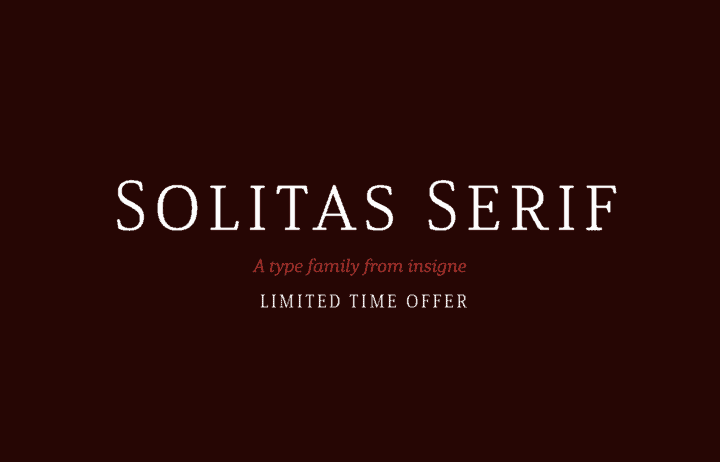
Solitas Serif Font Family
Aqui está uma descrição em português para a página de download da font Solitas Serif: Estou aqui a nova Solitas Serif, apresentada por insigne. Inspirado no design de insígnia, esta serif oferece uma opção mais suave e não tão rígida como outras fontes semifinais. Solitas Serif é perfeito para os designers que procuram um estilo serif menos formal e mais fluido, com serifs leves e bordas redondas. Seja você designer de blogs pessoais ou profissional, Solitas proporciona um toque suave a suas obras. A inspiração vem das curvas da famosa Solitas e do seu estilo semifinaleiro mais robusto (Solitas Slab). O resultado é uma fonte que transmite um charme discreto e contínuo. Este estilo de design oferece ao leitor uma experiência visual agradável, enquanto ainda mantém o bom design de serif que já conhecemos. Descubra agora Solitas Serif – sua próxima escolha para trabalhos profissionais ou criativos. Isso vai trazer vida e personalidade à forma e conteúdo de seu trabalho.